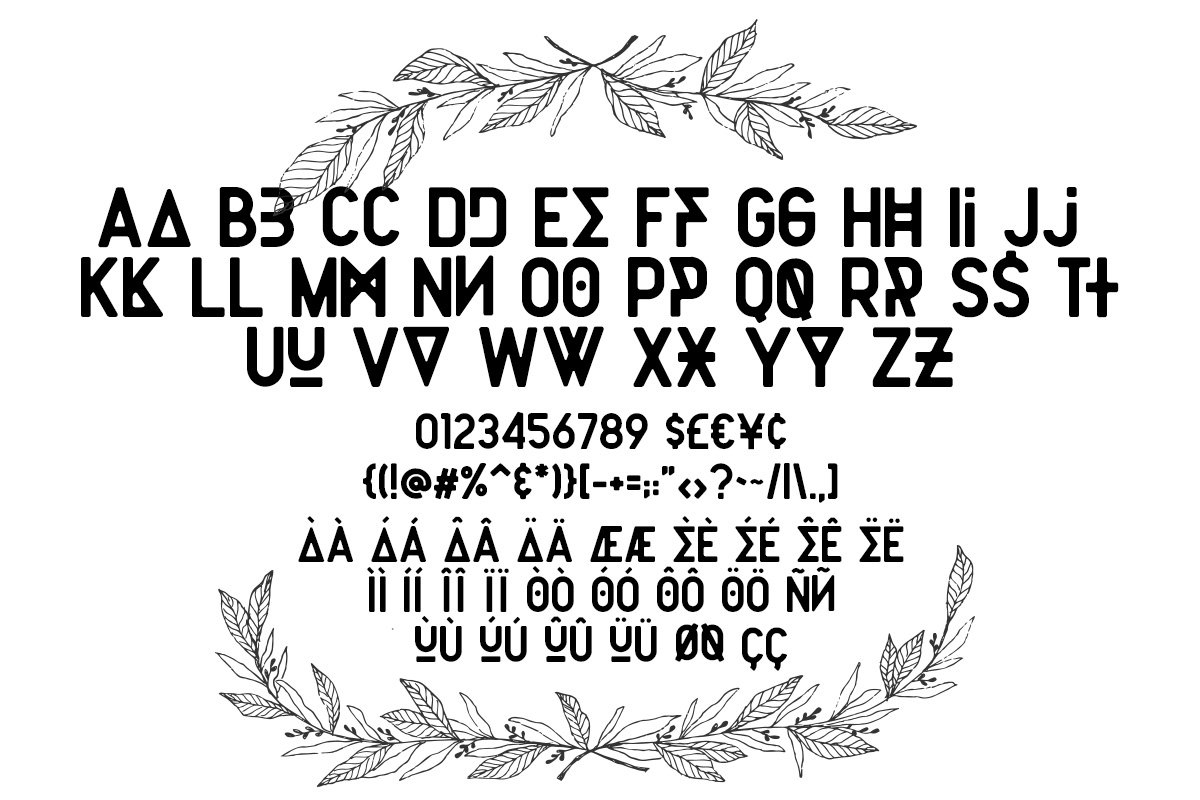
Share font Rogertype Việt Hóa cực đẹp
Font Rogertype Việt Hóa là một font chữ serif cổ điển đơn giản và gọn gàng. Hoàn hảo cho nhiều dự án khác nhau như: thiết kế trích dẫn, tiêu đề blog, áp phích, đám cưới, thương hiệu, biểu tượng, thời trang, may mặc, thư, lời mời, văn phòng phẩm, v.v.